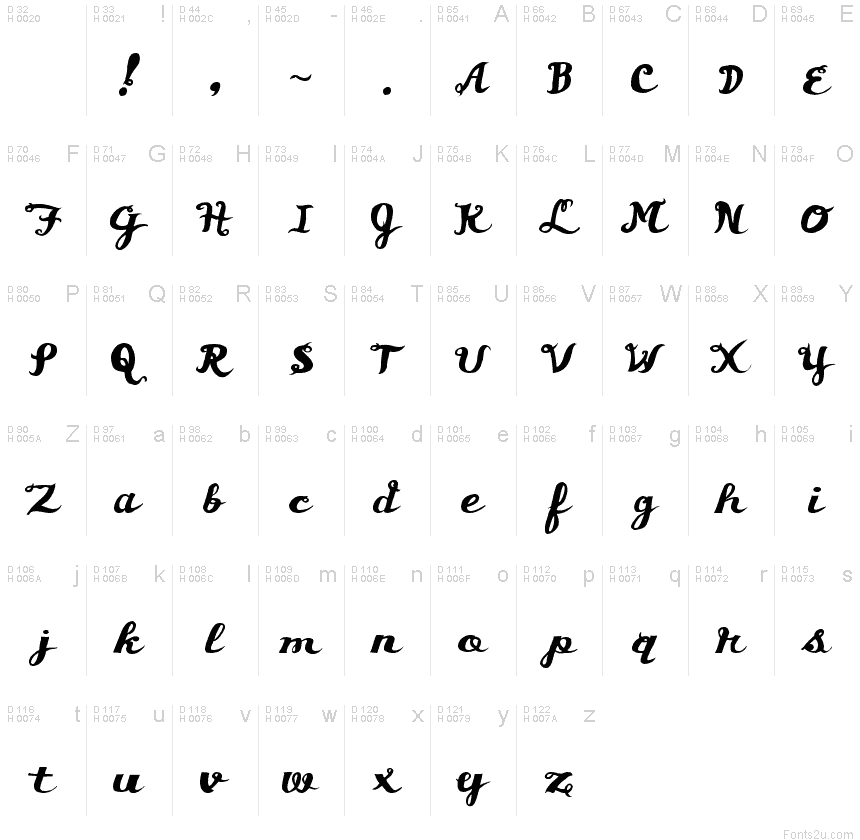
Asswipe من Schmopyright هو خط مجاني مكتوب بخط اليد يبدو فخمًا وأنيقًا للوهلة الأولى، لكنه يفاجئك بلمسة ماكرة. تندمج الخطوط السميكة المفعمة بالحبر في وصلات سريعة ومائلة، مما يمنحه طابع اللوحات المرسومة يدويًا في ساعة متأخرة من الليل. التباين بين منحنياته الحريرية واسمه الصريح يضفي على تصاميمك لمسة فكاهية، مرحة وفي الوقت ذاته راقية بشكل غريب.
يتألق خط Asswipe في ملصقات الحفلات، والمجلات المستقلة، وقوائم المشروبات في المقاهي، وبطاقات المعايدة المتمردة، وتصاميم القمصان، والمنشورات الجريئة على وسائل التواصل الاجتماعي. تتجمع الحروف في إيقاع كثيف ومخملي يسهل قراءته بأحجام كبيرة ويقفز من الصفحة. امزجه مع خط sans-serif هندسي بسيط في النصوص الصغيرة للحفاظ على التركيز حيث يجب أن يكون: في ذلك العنوان المكتوب بخط اليد، الصاخب والواثق.